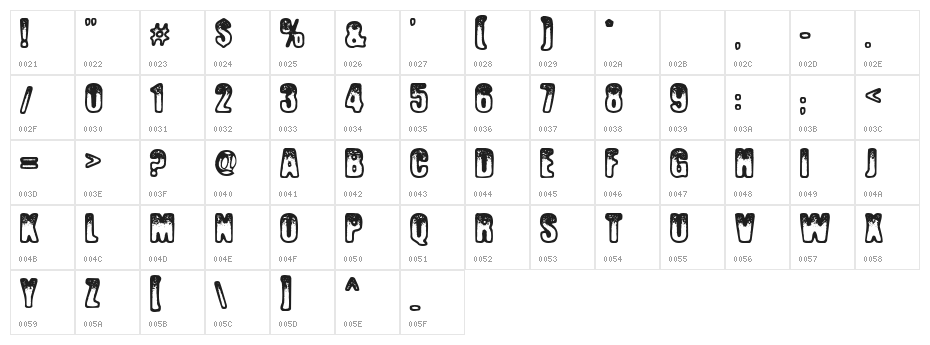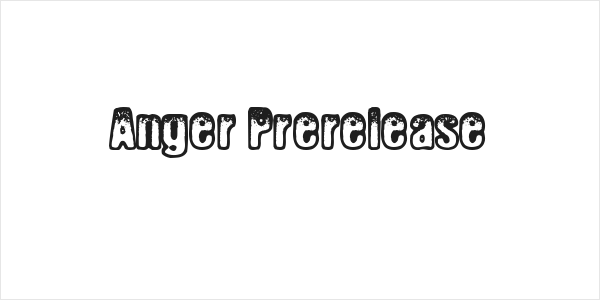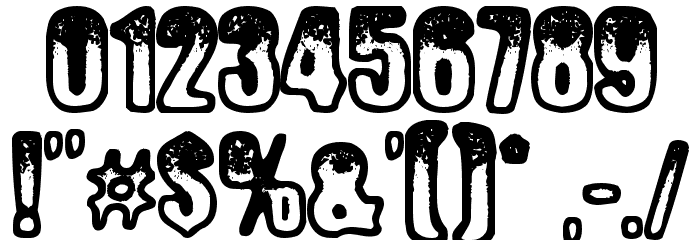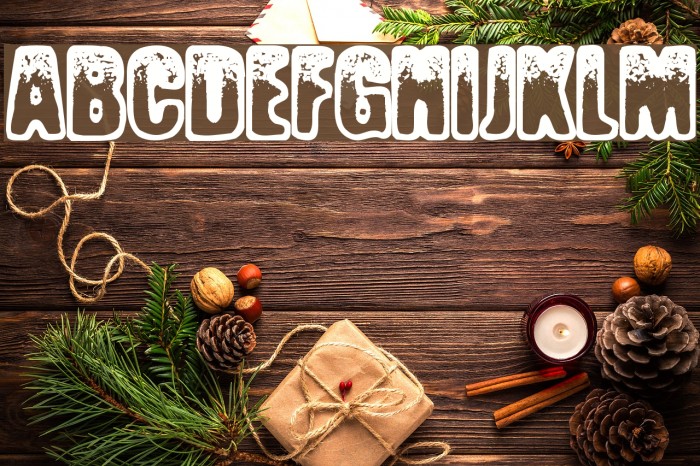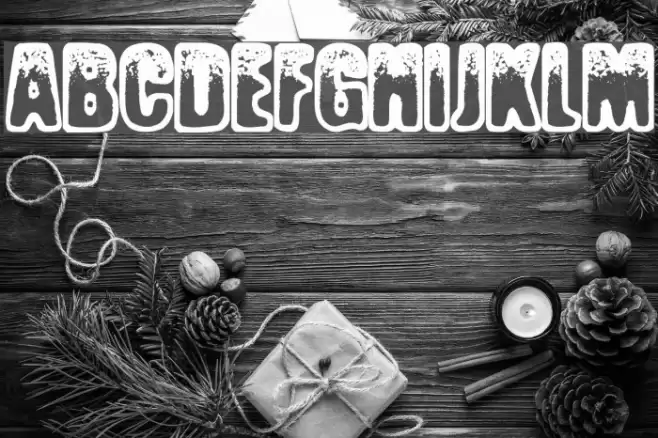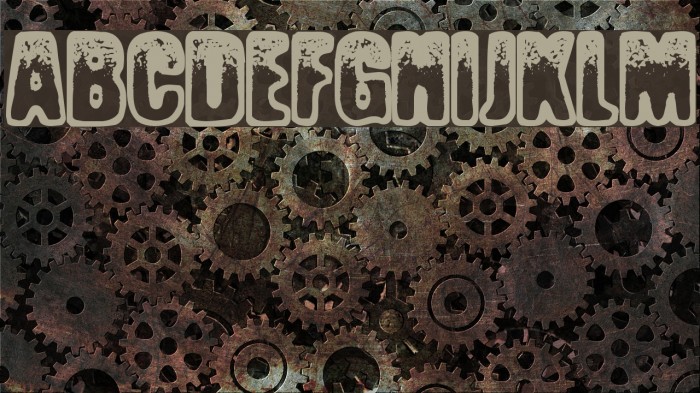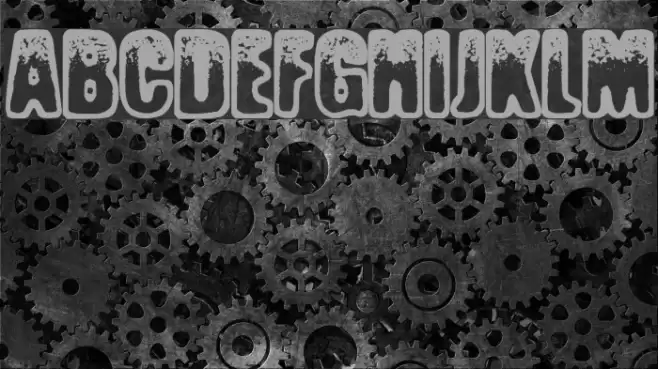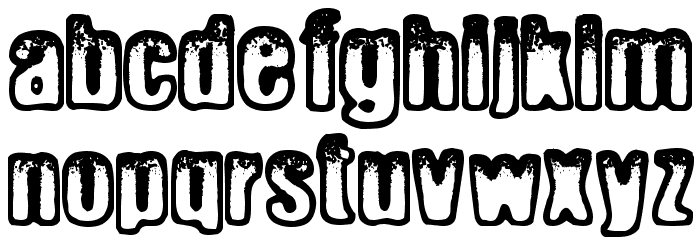
Anger Prerelease Font
✎ Distorted Eroded
| 全体的なスタイル | Grunge, Edgy |
| おすすめプロジェクト | Ideal for projects requiring a strong, edgy look such as music album covers, posters, or branding for extreme sports. |